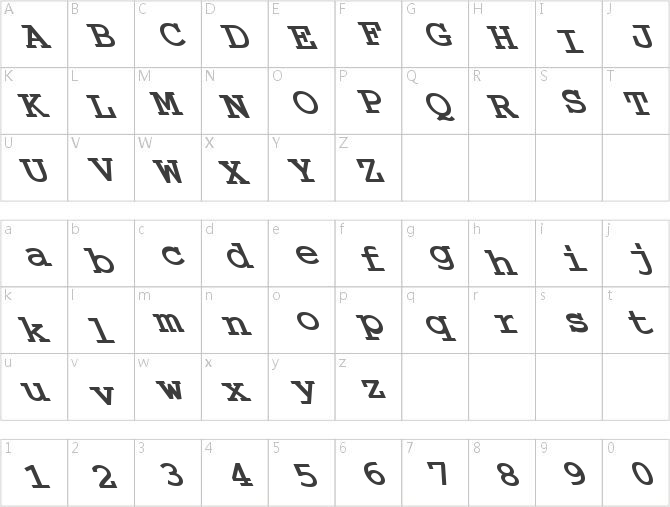
FZ DIGITAL 3 LEFTY 詳情頁
FZ DIGITAL 3 LEFTY
FZ DIGITAL 3 LEFTY字體字庫是一款讓人賞心悅目、百看不厭的英文字體,適合各類廣告和產(chǎn)品包裝設計應用,字體大小0.05MB,格式為ttf字體,上傳用戶是13226568769,作者/版權方為未知